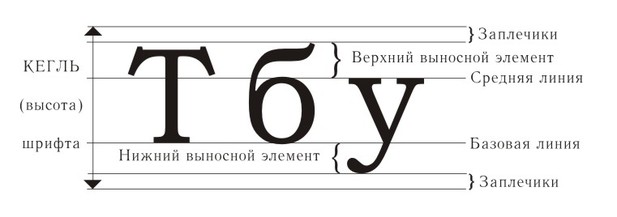
Размер шрифта ( кегль), его высота задается в пунктах. Пункт – единица измерения, принятая в полиграфии. Кроме пункта используется питч ( pitch) – количество символов, которое может быть напечатано на отрезке в один дюйм. Размер шрифта на принтере в пунктах определяет расстояние от верхнего края самого высокого символа до нижнего края самого низкого. Кегль включает высоту собственно буквы ( очко) и так называемые заплечики – свободные пространства над и под очком, образующие межстрочные промежутки. [1]
Размер шрифта определяется его высотой в пунктах и выбирается из множества, определенного для каждого вида шрифта, или устанавливается самим пользователем. [2]
Размер шрифта определяется высотой прописных ( заглавных) букв в миллиметрах.
Размер шрифта определяется высотой h прописных букв в миллиметрах. [6]
Размер шрифта ( кегль), его высота задается в пунктах. Пункт – единица измерения, принятая в полиграфии. Кроме пункта используется питч ( pitch) – количество символов, которое может быть напечатано на отрезке в один дюйм. Размер шрифта на принтере в пунктах определяет расстояние от верхнего края самого высокого символа до нижнего края самого низкого. Кегль включает высоту собственно буквы ( очко) и так называемые заплечики – свободные пространства над и под очком, образующие межстрочные промежутки. [7]
Размер шрифта определяется его высотой в пунктах и выбирается из множества, определенного для каждого вида шрифта, или устанавливается самим пользователем.
Размер шрифта ( кегль), его высота задается в пунктах. Пункт – единица, принятая в полиграфии. Размер шрифта на принтере в пунктах определяет высоту от верхнего края самого высокого символа до нижнего края самого низкого. [10]
Размер шрифта и расстояние между строками оценивают в пунктах. [11]
Размер шрифта h – величина, определенная высотой прописных букв в миллиметрах. [12]
Размер шрифта определяется высотой h прописных ( заглавных) букв в мм. [13]
Размер шрифта определяется высотой h прописных букв в миллиметрах. [14]
Размер шрифта
Ширина прописных букв Д, Ж, Ф, Ш, Щ, Ы, Ю равна их высоте. Ширина прописных букв М и Ъ примерно равна 6 / 7 высоты их. Ширина строчных букв ( кроме ж, м, т, ф, ш, щ, ъ, ы, ю) примерно соответствует 3 / 7 размера шрифта. Ширина строчных букв ж, м, т, ф, ш, щ, ъ, ы, ю примерно равна 4 / 7 размера шрифта. Ширина цифры 1 примерно равна 2 / 7 ее высоты. Толщина линий прописных букв и цифр примерно соответствует 1 / 7 размера шрифта. Толщина линий строчных букв примерно равна 1 / 10 размера шрифта. Прописная буква в слове со строчными буквами должна иметь толщину линий ту же, что и у строчных букв. В особых случаях допускается применение прямых букв и цифр ( без наклона к основанию строки), а также при недостатке места – более узких ( как прямых, так и наклонных) букв и цифр, ширина которых для данного размера шрифта берется по ближайшему меньшему размеру шрифта.
ГОСТ 2.304-81 «Шрифты чертежные» устанавливает обязательные для применения в машиностроительных чертежах начертания букв и цифр стандартным чертежным шрифтом.
Номер шрифта определяется высотой h прописных (!) букв в миллиметрах. Все остальные размеры букв и цифр определяются в зависимости от размера шрифта.
В таблице 6.1 приведены данные об относительных параметрах шрифта и вычислены соответствующие параметры в мм для шрифта 10.
Таблица 4.1
| Параметры шрифта | Относительный размер | Шрифт 10, мм |
| Ширина цифр и букв: з ц 3 5 Г Е З С б в г д е и к л н о п р у х ч ь э я 2 4 6 7 8 9 0 Б В И К Л Н О П Р Т У Ч Ь Э Я а м ц ъ ы ю А Д Х Ц Ы Ю ж Ж М Ш Ъ т ф ш Щ щ Ф № | 4/14 h 5/14 h 6/14 h 7/14 h 8/14 h 9/14 h 10/14 h 11/14 h 12/14 h | 2,8 3,6 4,3 5,7 6,4 7,1 7,8 8,5 |
| Высота строчных букв | 10/14 h | 7,1 |
| Расстояние между буквами | 2/14 h | 1,4 |
| Минимальный шаг строк | 22/14 h | 15,7 |
| Минимальное расстояние между словами | 6/14 h | 4,3 |
| Толщина линий шрифта | 1/14 h | 0,7 |
При выполнении надписей крупного размера (шрифт 10 и выше) необходимо нанести сетку в виде наклонных тонких линий с учетом ширины каждой буквы или цифры.
Для более мелких размеров шрифта достаточно провести лишь две параллельные горизонтальные линии и под углом 75°, через 10‑12 мм наклонные линии для контроля правильности наклона надписей. Буквы и цифры следует выполнять по частям, допуская движение руки только по двум направлениям – сверху вниз и слева направо.
Прежде чем приступить к заполнению формата, необходимо предварительно поупражняться в правильном начертании букв на черновике, так как без достаточной практики удовлетворительно выполнить шрифт очень трудно.
При выполнении чертежей всех последующих тем надписи (буквенные и цифровые) должны выполняться строго в соответствии с указанным ГОСТом.
Для того чтобы выполнить надпись симметрично относительно боковых сторон рамки, можно с помощью таблицы 6.1 рассчитать ширину строки. Например, ширина строки НГТИ составляет